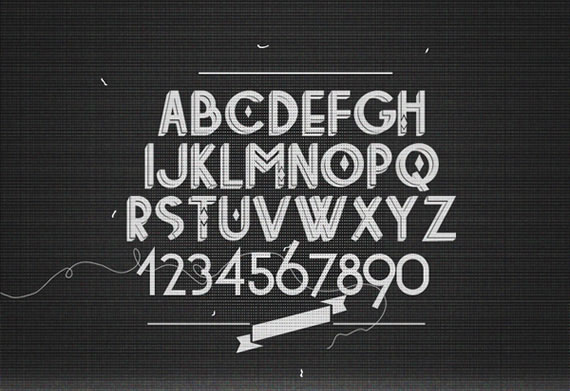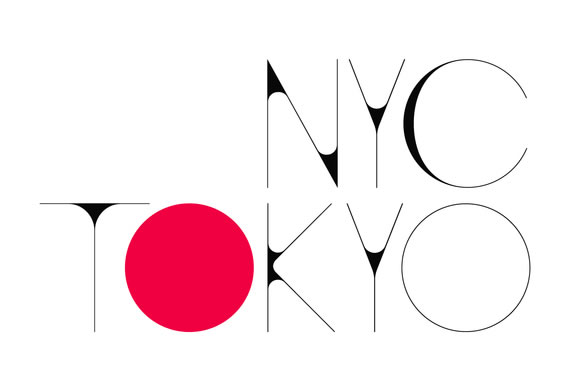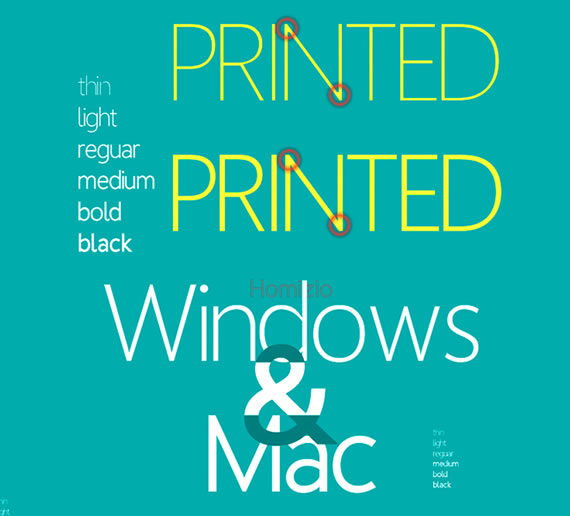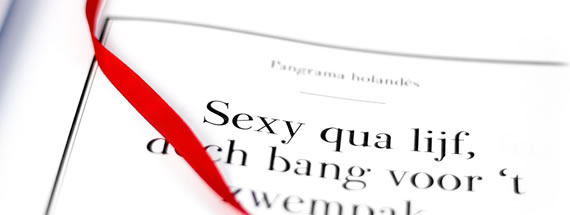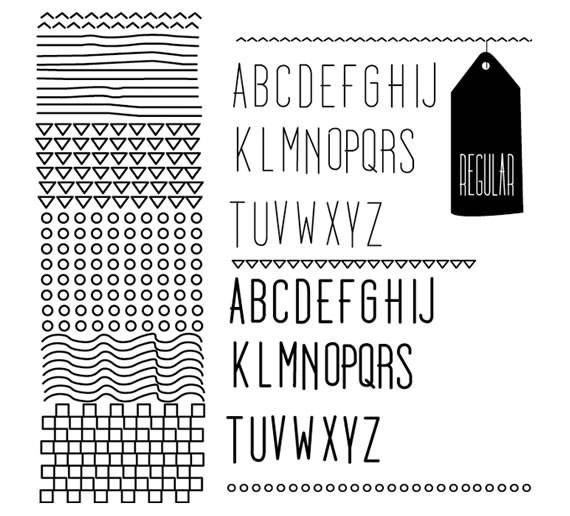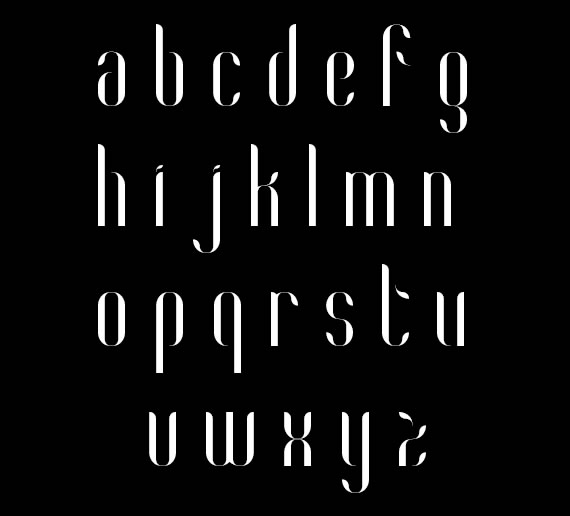
El mes pasado estuve recolectando algunas fuentes gratuitas que llamaron mi atención entre todas las que se recomiendan semana a semana, la siguiente es una colección de fuentes tipográficas para diferentes tipos de uso, aunque por lo general encontrarán que son más útiles para letreros y textos destacados.